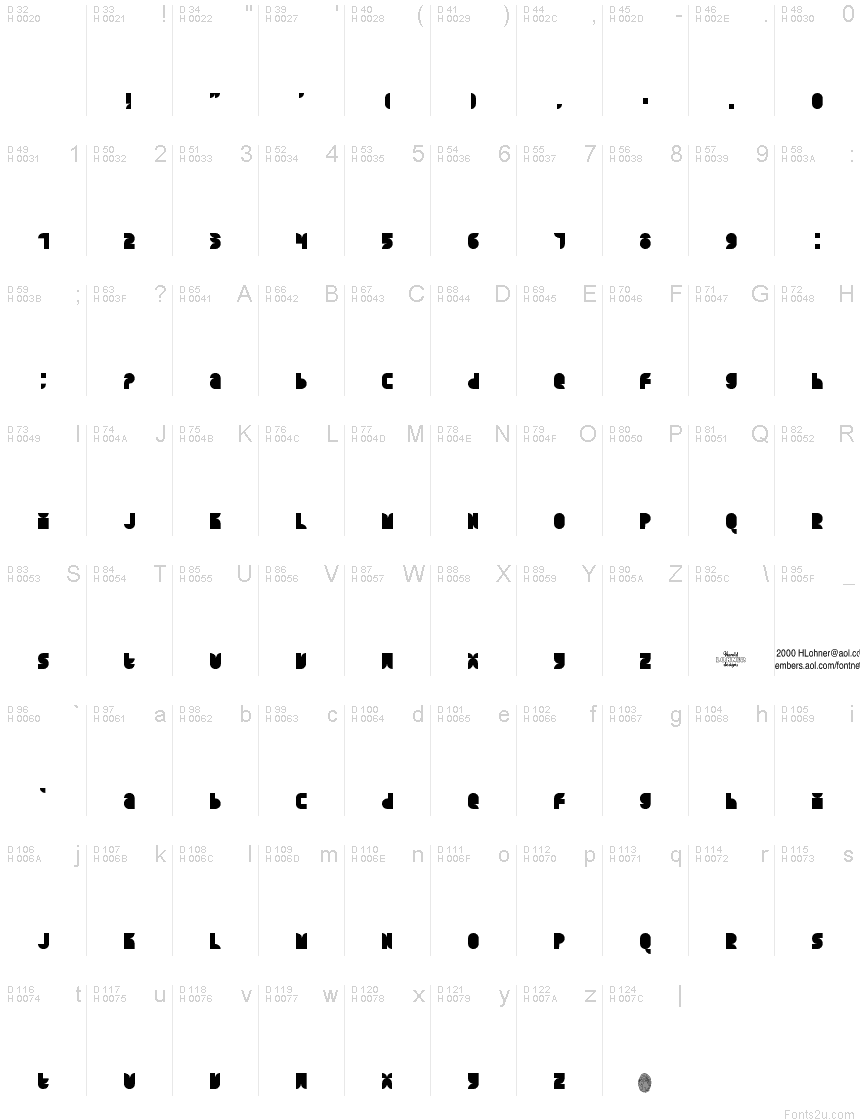
Quarterround Solid è il font display gratuito di Harold Lohner, che cattura appieno l'atmosfera degli anni '70 con le sue curve corpose e i tagli a quarto di cerchio. Le lettere sono morbide ma pesanti, con forme esterne arrotondate che incontrano tagli netti e giunture squadrate; l'intero alfabeto richiama uno stile di segnaletica modulare e audace, ben lontano dalla solita nostalgia retrò.
È perfetta per copertine di dischi, titoli di poster, branding di bar, packaging e titoli dove è richiesta quella silhouette morbida e tipica dell'epoca. Essendo un font gratuito, è ideale anche per loghi, brevi testi di copertina e monogrammi, poiché le forme grandi e arrotondate rendono al meglio in contesti sintetici.